中秋海报设计教程,送你8个超好用的技巧!
后天就是中秋节了,今天小编为大家收集了一大波中秋海报。在设计中秋海报过程中,如何运用创意来满足甲方的要求?下面总结了八个技巧让大家灵感爆棚。
01
插画类
02
实物场景类
03
生活场景类
很多互联网品牌早已将生活场景作为传播的“常规操作”。借助互联网大数据,稳抓用户生活轨迹,透过镜头精准切割出用户生活场景。作品多数采用丰富温柔的形式展开的创作,将生活的一些情节定格与插画中。以场景触发用户情感,最终引发用户共鸣。
04
字体设计类
通过重新设计的字体,以简明而突出的方式能触动消费者的心理,让画面创造独特性更强。
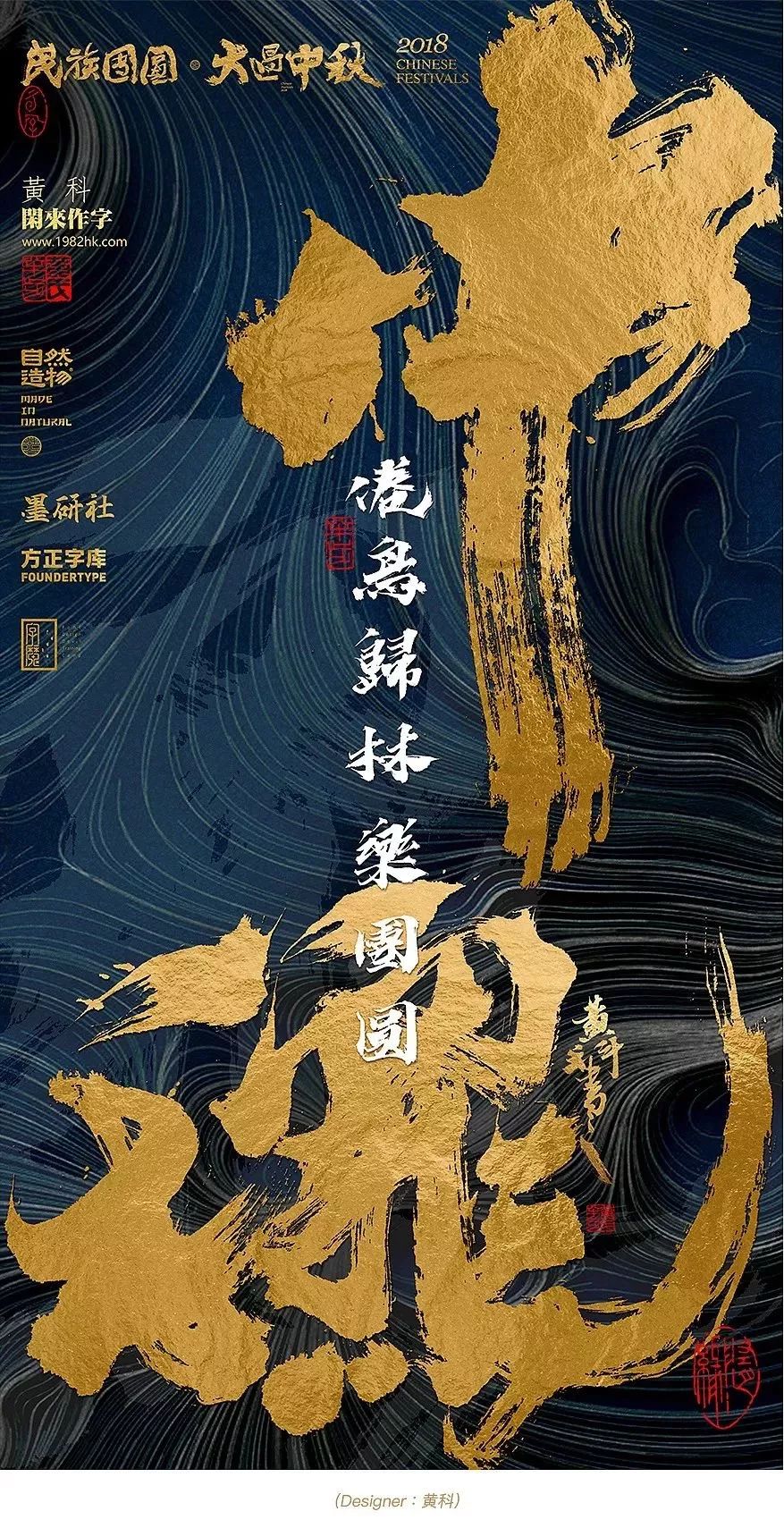
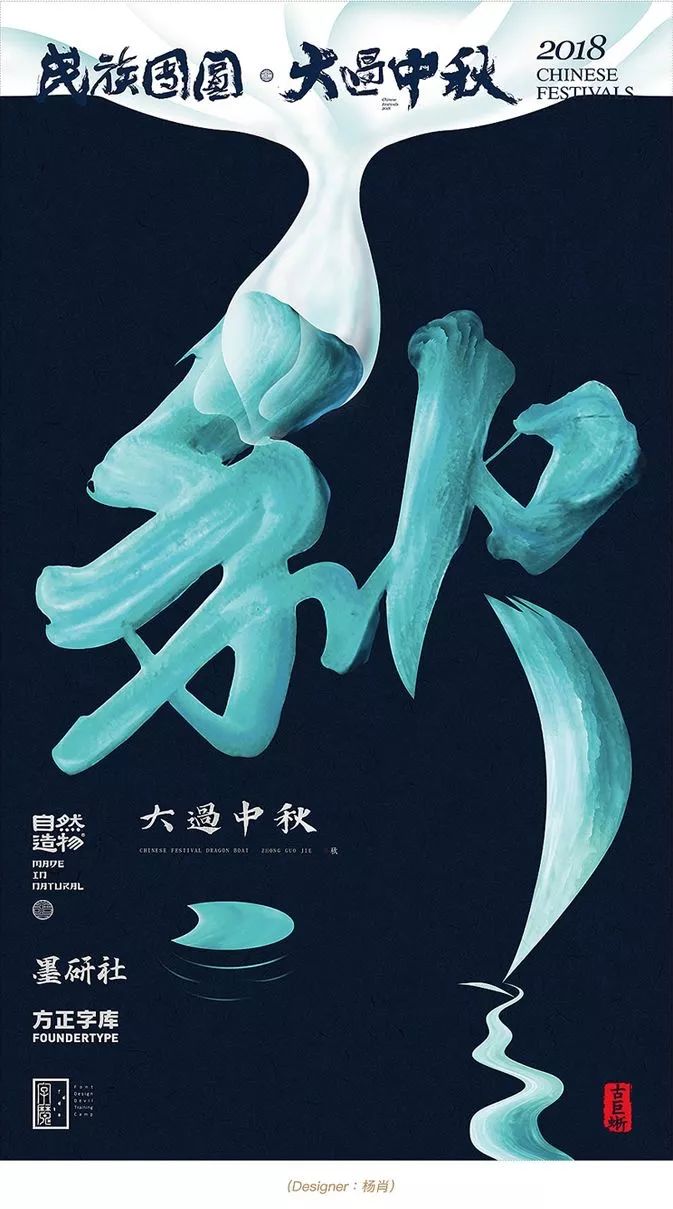
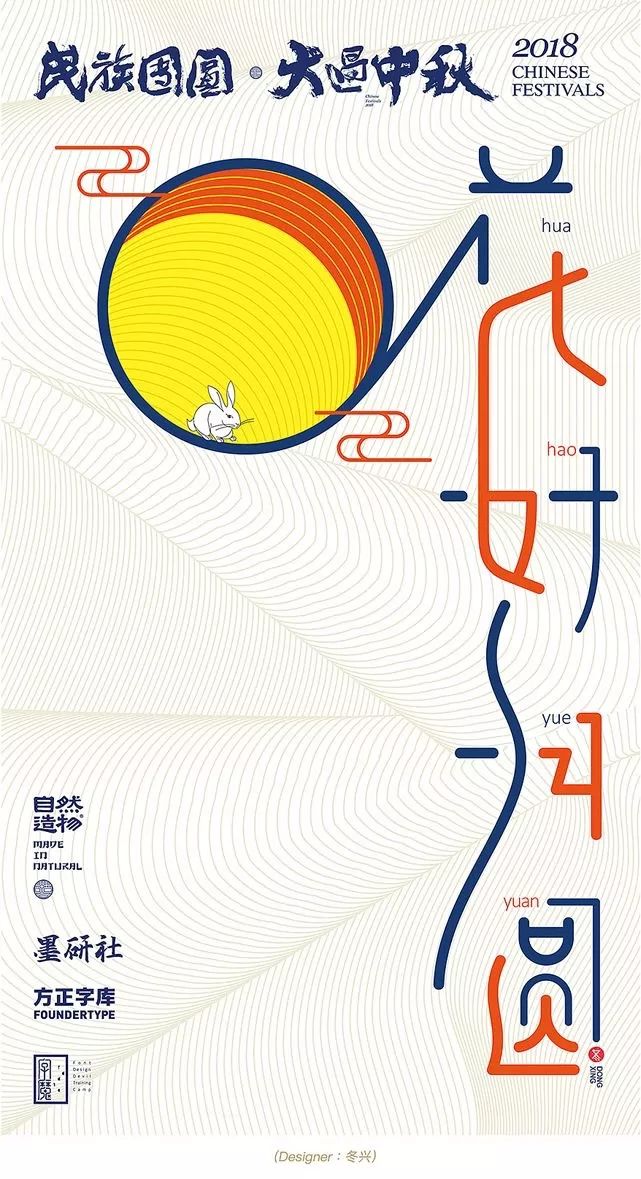
05
异质同构类
06
符号类
07
置换类
将某个元素替换成产品图形,其方法也有比喻的意义。这一手法成立的条件是两个元素在外形上要有一定的相似度。
08
其他